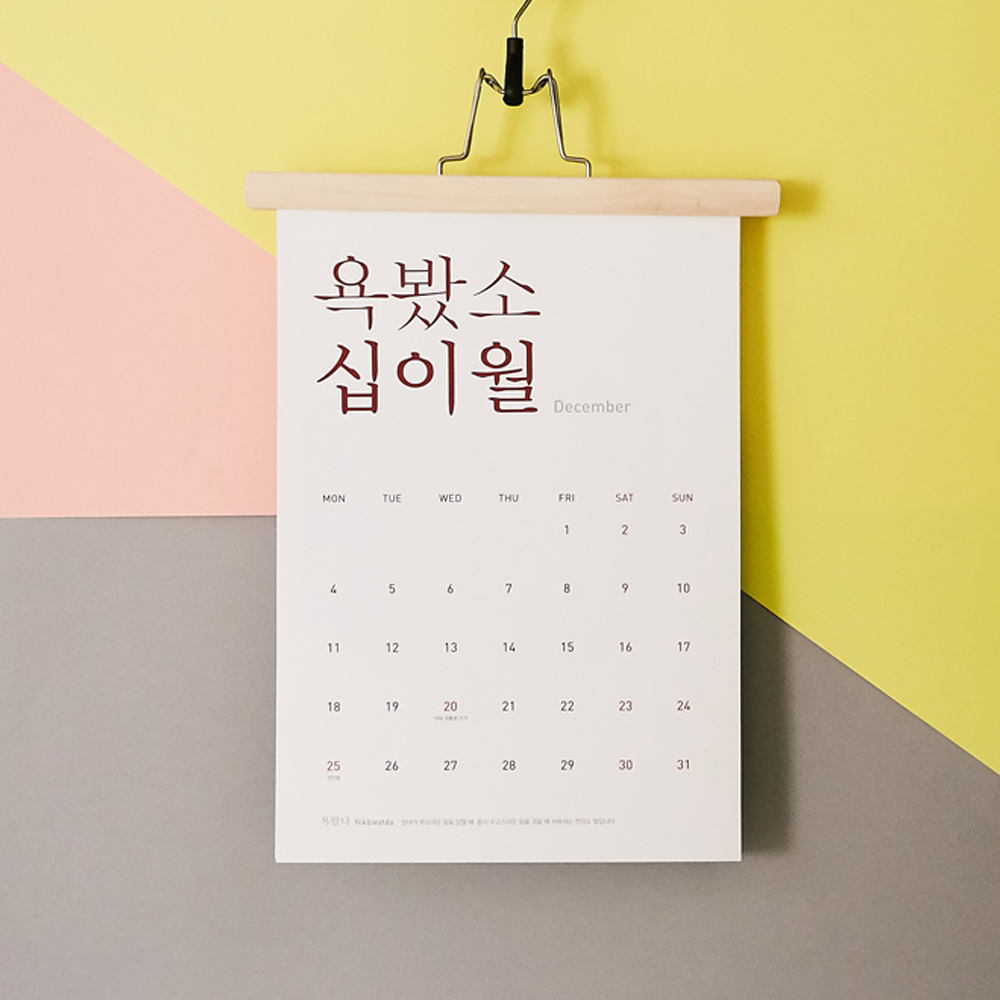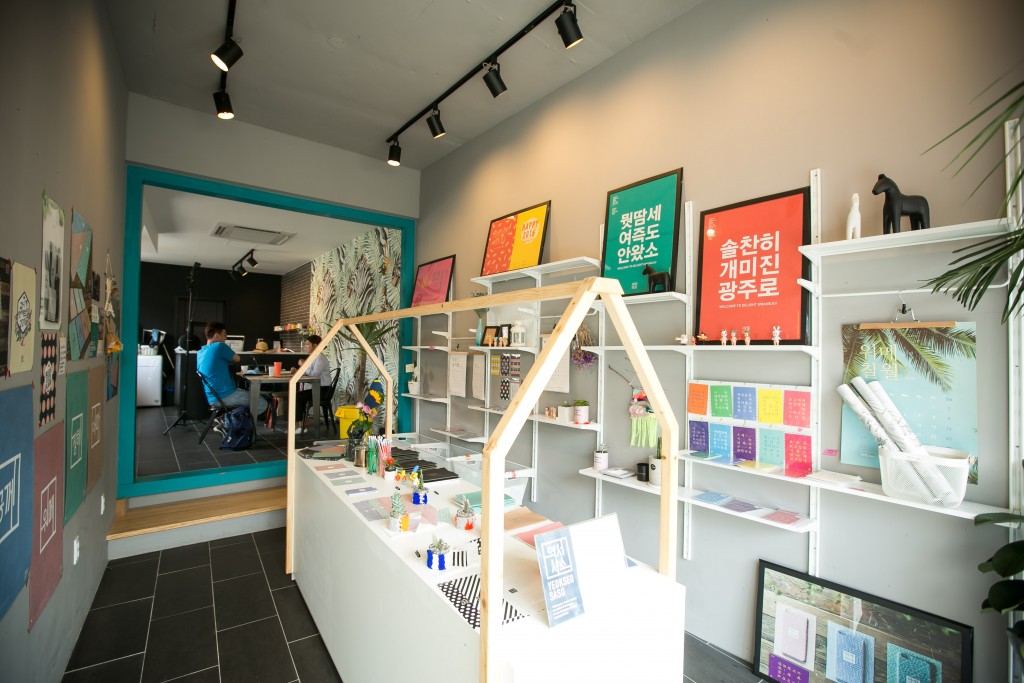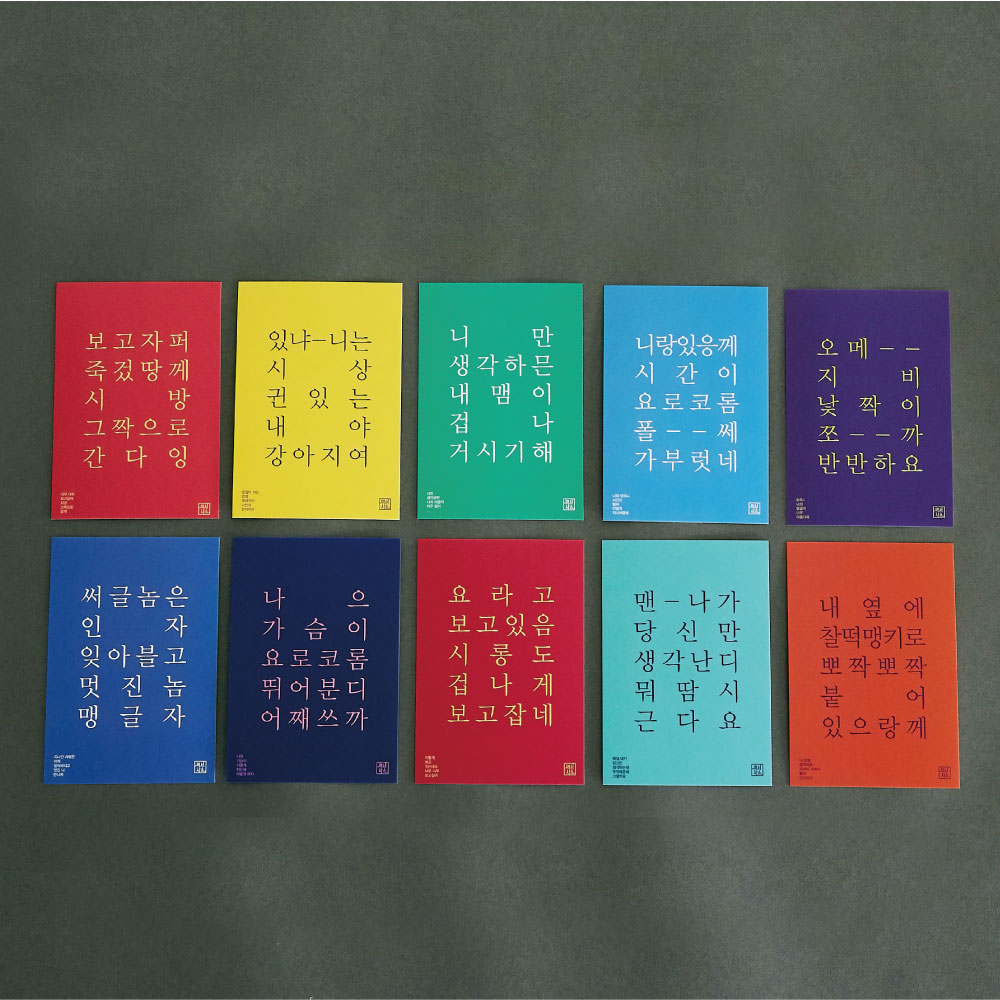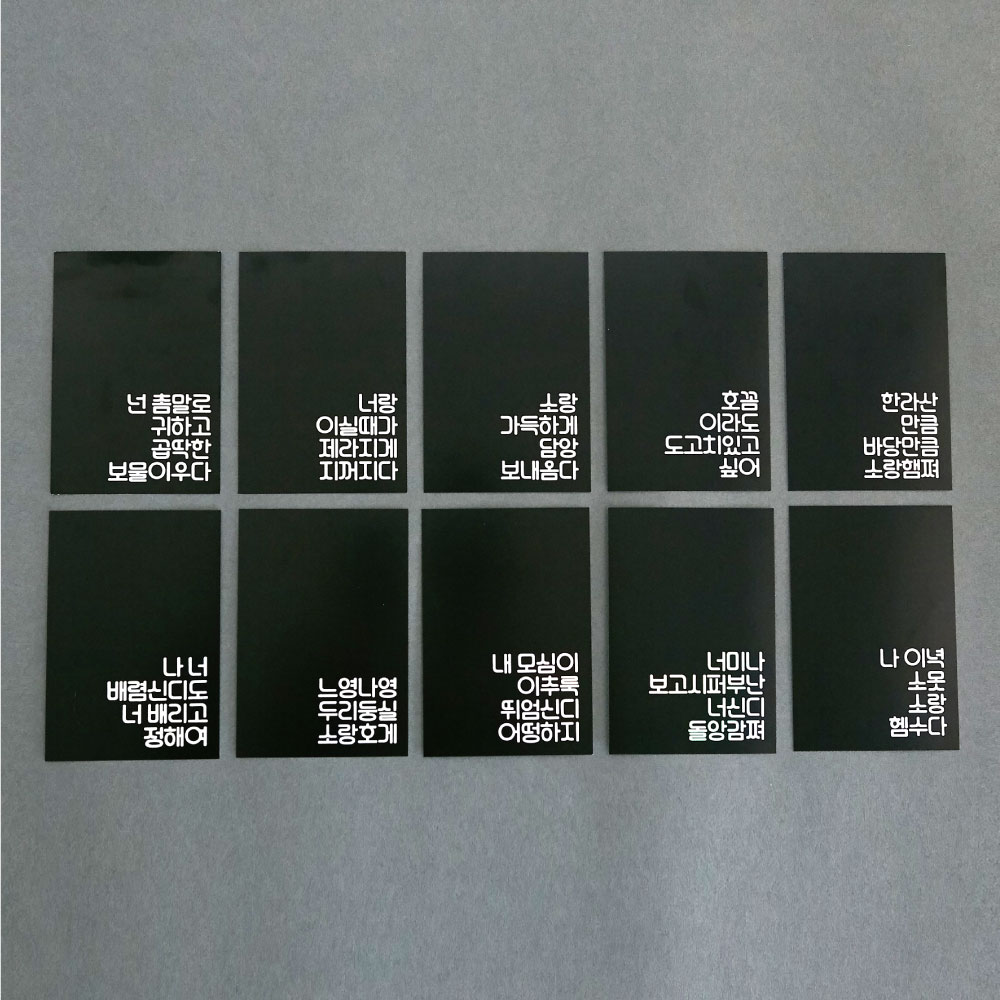
‘워메’ 정감 가는 사투리 디자인으로 세상을 놀라게 한 ‘김효미·김진아’ 대표
구수한 지역 방언을 트렌디한 타이포그래피 디자인 제품으로 탄생시킨 두 디자이너가 있다. 그 주인공은 바로 바비샤인의 김진아 대표이다. 김 대표는 3년전 광주광역시에 위치한 1913송정역시장에서 ‘역서사소’라는 상점을 김효미 공동대표와 함께 열어 동업 중이다. 각종 SNS에서 화제가 된 제품을 디자인·판매해 고공행진 중인 그녀들을 만나 이야기를 듣는 코너를 마련했다.
안녕하세요. 광주광역시에 위치한 시각디자인 기업 ‘바비샤인’과 디자인 상점 ‘역서사소’를 운영하는 김진아입니다. 우리만의 브랜드를 만들어 우리의 모습을 가장 잘 드러낼 수 있는 것을 고민해왔습니다. 그러다가 일상에서 사용하는 우리 지역의 사투리가 타 지역민에게 일부 부정적으로 다가오고 촌스럽게 여겨지고 있다는 것을 알게 됐습니다. 이후 사투리의 우리네 정과 마음이 담긴 뜻을 알리고자 했고 타이포그래피를 통해 사투리 안에 담긴 본연의 뜻을 돋보이게 하는 디자인 제품을 선보였습니다.
역서사소가 세상에 알려진 것은 올해로 3년 차가 되어가고 있습니다.
처음에는 “이게 뭐야”, “이런 것도 있네”와 같은 고객의 반응이 대다수였지만 최근엔 멀리서 찾아오시는 분들도 많아지고, 남녀노소 구분 없이 관심을 갖고 보아주셔서 감사할 따름입니다. 그리고 주변 이웃으로부터 우리 지역의 사투리를 예쁘게 디자인해주어 고맙다는 인사도 종종 듣습니다.
4차산업혁명의 시대가 다가오면서 아날로그보다는 디지털 의존도가 높아지는 가운데 아날로그의 정겨운 감성과 느리게 사는 삶이 좋다는 것을 느끼고 있습니다. 손으로 직접 쓰고 마음을 전달하는 것이 백 마디의 말과 기계 속에서 보이는 마음보다 더 와 닿는다는 것을 저와 고객분들이 함께 느끼고 있습니다.
최근 전라도 사투리를 활용한 제품뿐만 아니라 제주도와 경상도의 사투리 고백엽서도 출시가 되었습니다.
이외에도 최근 SNS와 소셜 커머스를 통해 인기를 얻은 ‘사투리 달력’이 있는데요.
‘사투리 달력’은 단순하지만 재치 있는 전라도 고유의 사투리 문구나 문장으로 그달의 감정을 표현했고 그 사투리의 의미를 하단에 소개하여 소비자들의 호응을 얻고 있습니다. 또한 달력 후면의 그래픽 디자인을 개인의 취향에 맞게 활용할 수 있도록 해 실용도를 높였습니다.
사투리의 뜻을 본 후 재미있어 하시는 분들이 대다수고 선물하기 위해 대량으로 구매해가시는 분들도 점차 늘어났습니다. 지역을 대표할 만한 상품이 없었지만 우리 제품이 전라남도 그리고 광주광역시의 대표가 된 것 같아 자부심을 느낄 때가 많습니다.
일상생활에서의 사용하는 언어와 더불어 각 지역의 역사를 되돌아볼 수 있는 좋은 의미를 가진 사투리를 좀 더 공부해서 다양한 언어들로 구사된 제품군을 추가로 만들어 보고 싶습니다.
그리고 향후에는 지역에서 활동 중인 제품디자이너나 뜻을 함께하는 기업과 다양한 협업을 시도해보려 합니다. 그래서 우리 지역의 언어를 더 많은 사람들에게 알리고자 노력할 것이고 일상 속에 스며들 수 있도록 다양한 제품으로 찾아뵐 계획입니다.
‘세상을 바꾸는 사투리’라는 슬로건을 내걸고 역서사소 운영을 시작했습니다. 사투리는 더 이상 촌스럽기만 한 것이 아니라 그 안의 지역의 삶과 역사를 전하고 타 지역민과의 교류를 하게 하는 매개체가 되기를 소원합니다. 이로써 지역감정도 해소되길 바라는 마음입니다. 사투리는 또한 우리가 지키고 보존해야 할 언어이자 소중한 자원이라는 것을 알리는게 우리의 바람입니다.